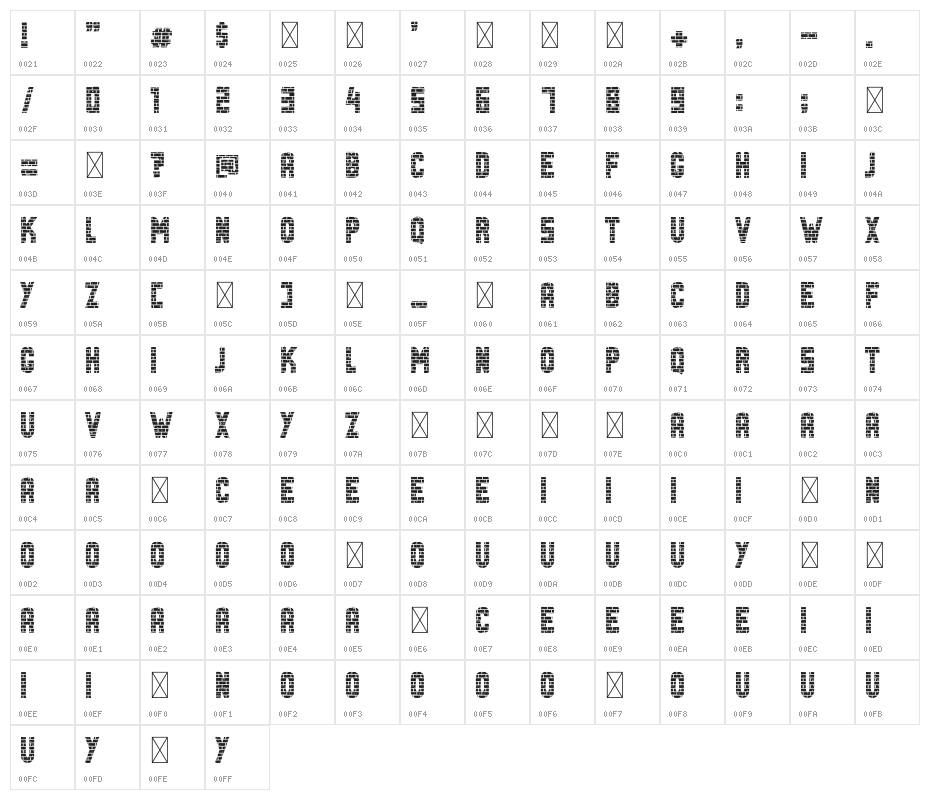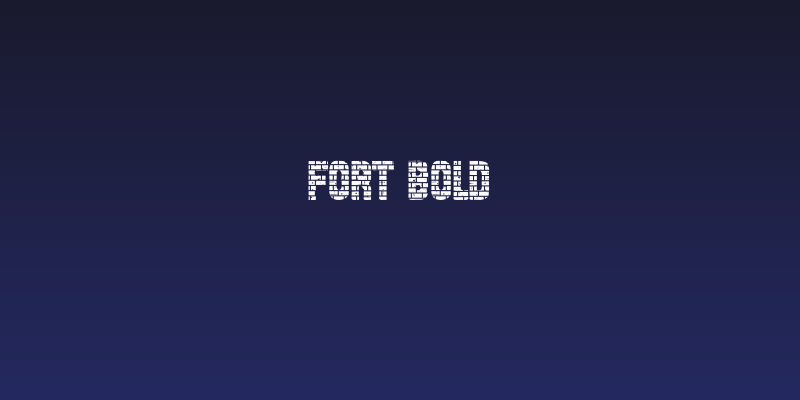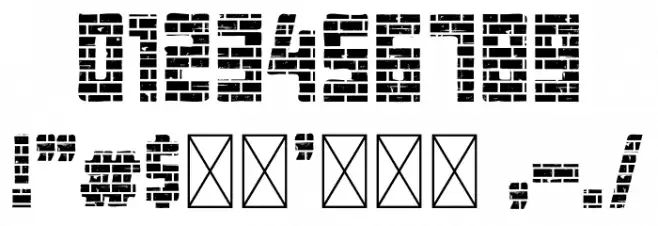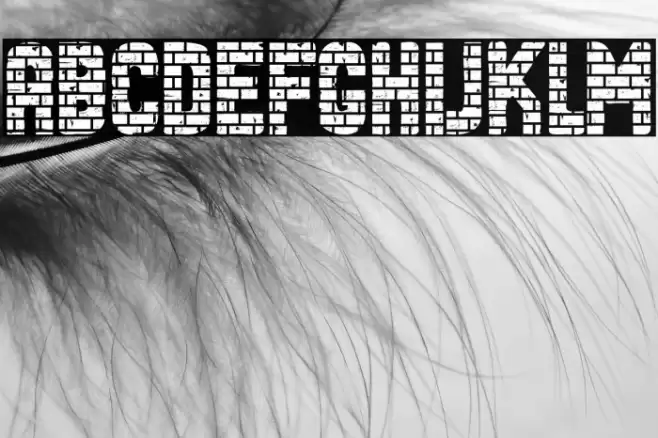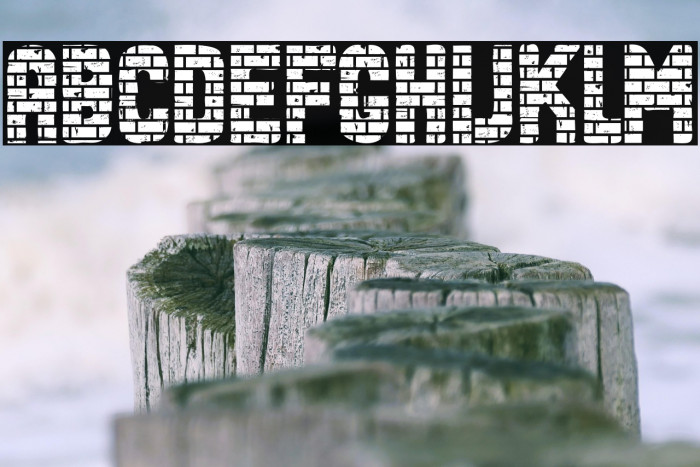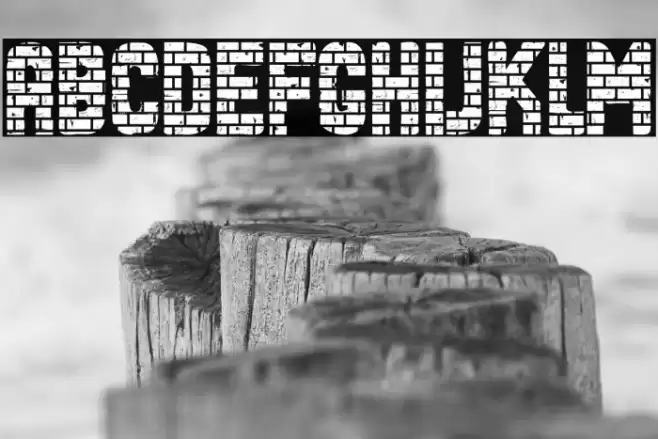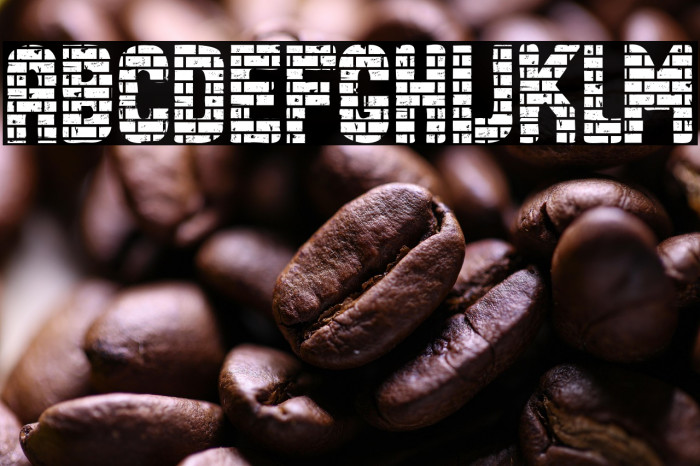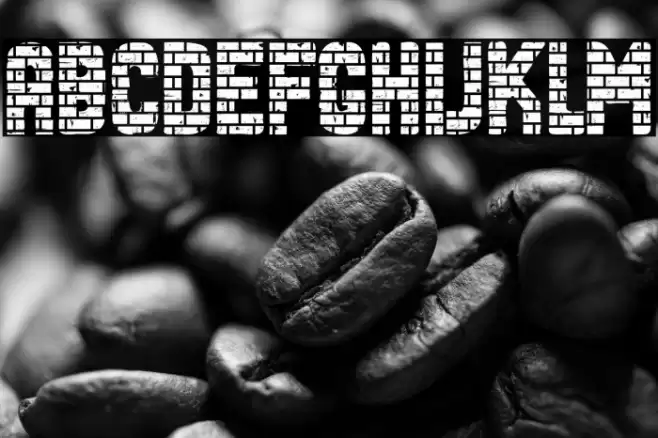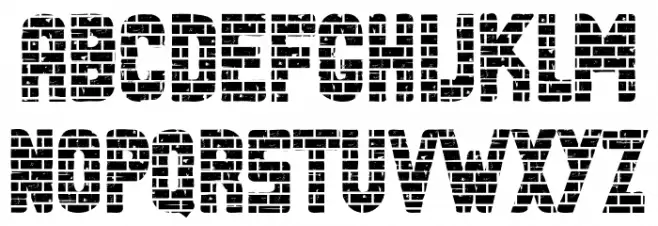
Fort Bold Font
| Style général | Industrial, Decorative |
| Projets proposés | Ideal for posters, headlines, branding, and any design needing a strong, industrial aesthetic. |